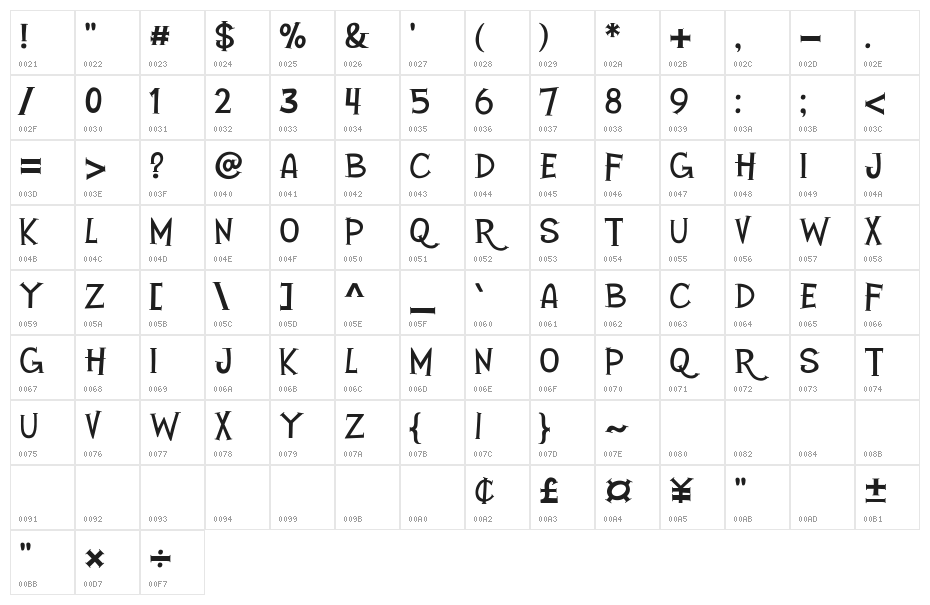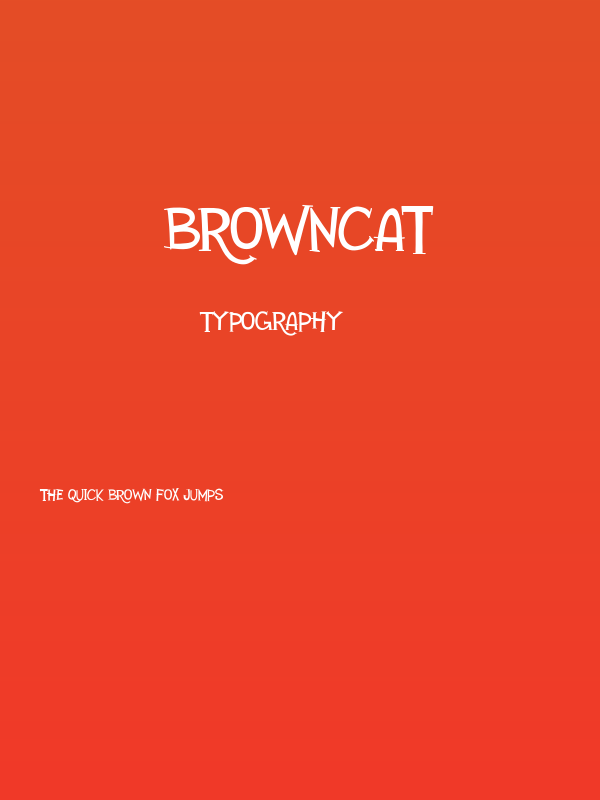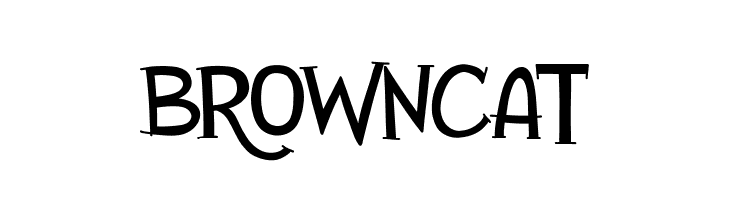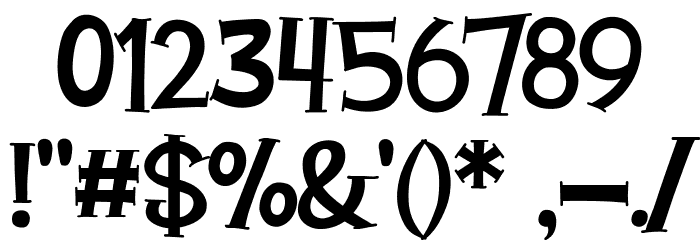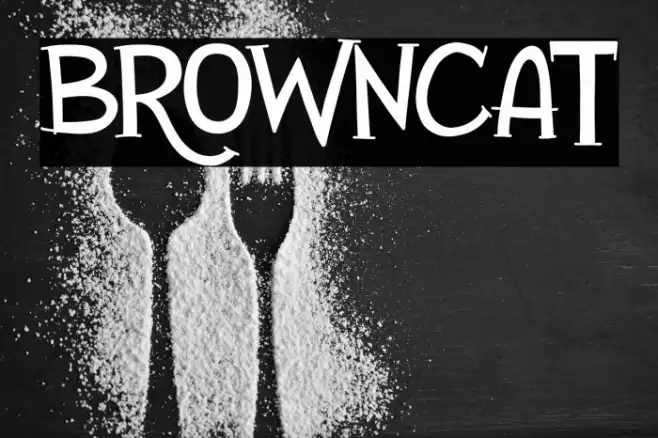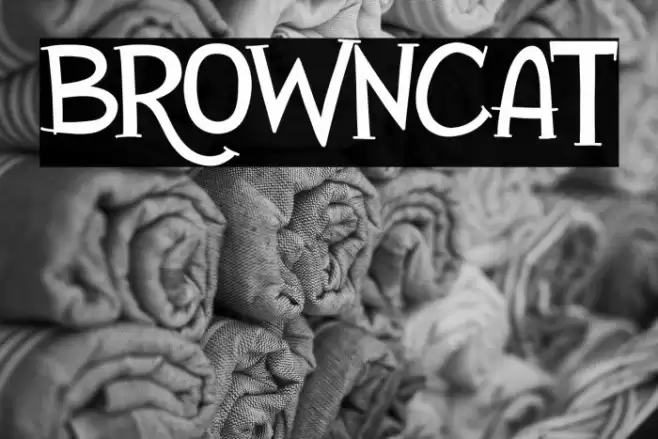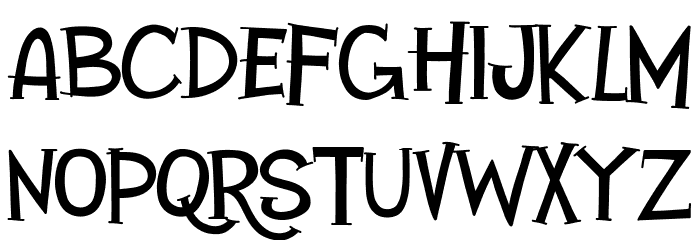
Browncat Font
| Gesamtstil | Playful |
| Vorgeschlagene Projekte | Ideal for children's books, comic strips, playful branding, and creative posters. |